Adobe Fontsに、アニメ「⿁滅の刃」でも使われている「昭和書体」の「黒⿓爽」「⼼⿓爽」のフォントがやってきました。思った以上に鬼滅感……!
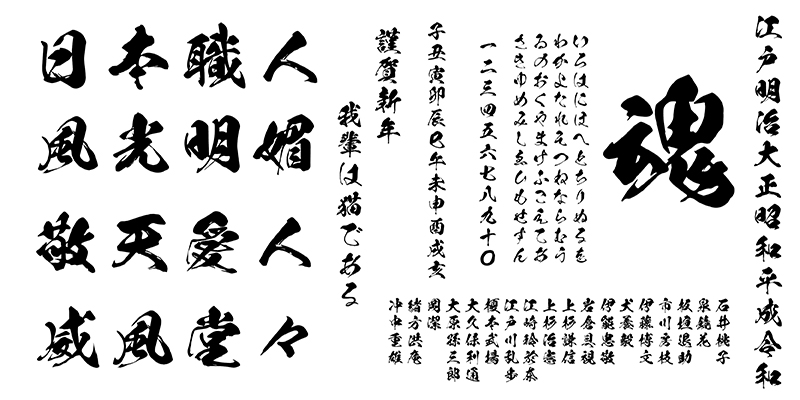
「黒龍」は、牡の龍が暗雲立ち込める空を荒々しく漂うさまをイメージして作られた筆書系デザイン書体。「太い線と細い線が入り混じる緩急のついた画線は、まるで猛々しい龍の感情の抑揚を表わしているかのようです」という説明があるように、打ち込むだけでかなり躍動感ある雰囲気になります。
なお、今回収録される「KSO黒龍爽」は、黒龍のカスレを少なくし容量を抑えたものなので、カッティングや動画にも使いやすくなっているそうですよ。
そのほか、手描きのヒグミンフォントや大日本印刷(DNP)からは「秀英にじみ初号明朝」「秀英にじみ明朝」が追加。Font1000からは34ものフォントが加わり、Adobe Fontsで使える日本語フォントは500以上になりました。登録したフォントはWordやExcelなどAdobe製品以外でも使えます。